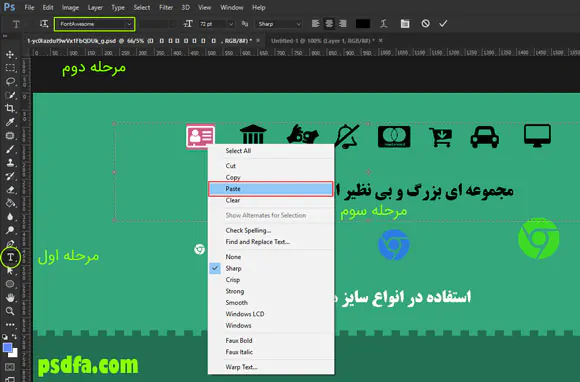
شاید تا به حال در بعضی از سایت ها یک سری از اشکال و آیکون ها به چشم شما خورده باشد که بخواهید از آن ها در محیط فتوشاپ یا بعضی از نرم افزار ها استفاده کنید . اما وقتی برای ذخیره این آیکون ها در صفحه وب ، راست کلیک می کنید گزینه ای به عنوان Save image as … ظاهر نشود . خب دلیل آن واضح است چرا که این نوع آیکون ها در واقع عکس یا تصویر نیستند . آن ها هم مانند سایر نوشته ها و متن های یک صفحه وب ، یک نوع فونت می باشند . نام این نوع فونت Awesome می باشد که در طراحی صفحات وب به دلیل کیفیت بالا و حجم کم و خیلی از مزیت های دیگر از این نوع فونت و آیکون استفاده می شود. مانند سایت پی اس دی فا که می توانید این آیکون ها را در گوشه و کنار سایت مشاهد کنید.
همانطور که گفته شد این آیکون ها از نوع فونت می باشند پس شما از آن ها فقط در تک رنگ می توانید استفاده کنید. یعنی فقط به عنوان آیکون های فلت ( تخت ) می توانید در پروژه های خود از آن ها بهره گیرید . همچنین هر چه قدر این وکتورها را بزرگ کنید از کیفیت آن ها کم نخواهد شد و کیفیت اصلی خود را حفظ خواهند کرد.
طرز استفاده از آیکون های فونت Awesome در محیط فتوشاپ